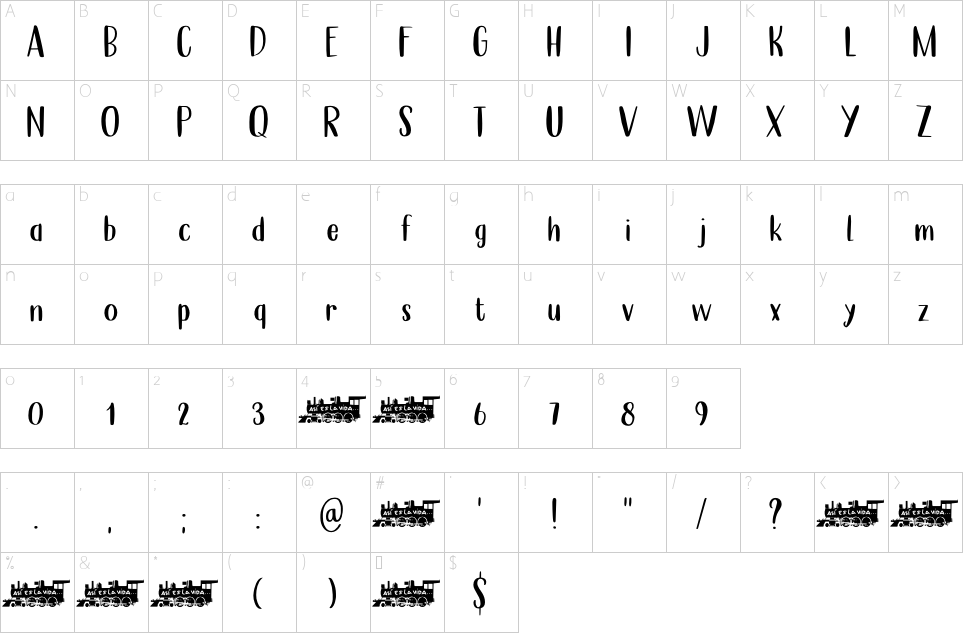
A fonte ‘Perfect Day’ é uma escolha perfeita para aqueles que buscam uma fonte elegante e confortável para projetos gráficos. Desenvolvida por Hanoded, esta fonte é uma excelente opção para criar designs em Windows e Mac. Com uma aparência suave e harmoniosa, ela combina facilmente com diversas tipografias para criar ambientes de design amigáveis e agradáveis ao usuário. Com mais de 19.800 downloads, a ‘Perfect Day’ provavelmente já está fazendo parte do seu portfólio de fontes. Se procura uma fonte para seus projetos, é provável que esteja procurando justamente o que a ‘Perfect Day’ pode oferecer. Seja para fins pessoais ou profissionais, a ‘Perfect Day’ é uma fonte que não só enriquece seu design, mas também torna-o mais atraente e agradável aos olhos do usuário. Descubra agora mesmo a ‘Perfect Day’ e inovar no seu design de forma elegante e única.